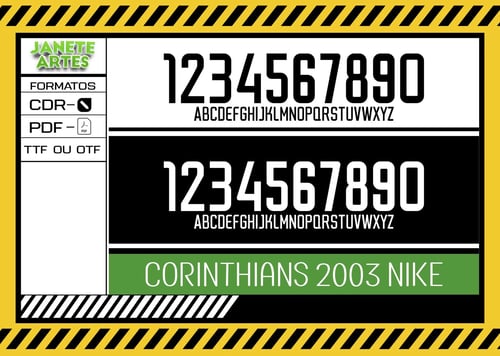
Uma história de paixão e estilo no futebol 🖤⚽
Você já imaginou vestir uma camiseta que traduz toda a história e emoção de um dos maiores times do Brasil? A Fonte de Time Tipografia Corinthians 2012 traz exatamente isso! Imagine João, um torcedor apaixonado que queria surpreender seus amigos do futebol com camisas personalizadas. Ele encontrou esta fonte, baixou o arquivo e criou peças incríveis para o grupo do bairro, que virou sensação em todos os jogos e encontros.
- Design fiel à tipografia usada pelo Corinthians em 2012.
- Perfeito para personalizar camisetas, camisas e blusas, dando um toque autêntico e personalizado.
- Para eventos ou torcidas, crie conjuntos com nomes e números usando esta fonte.